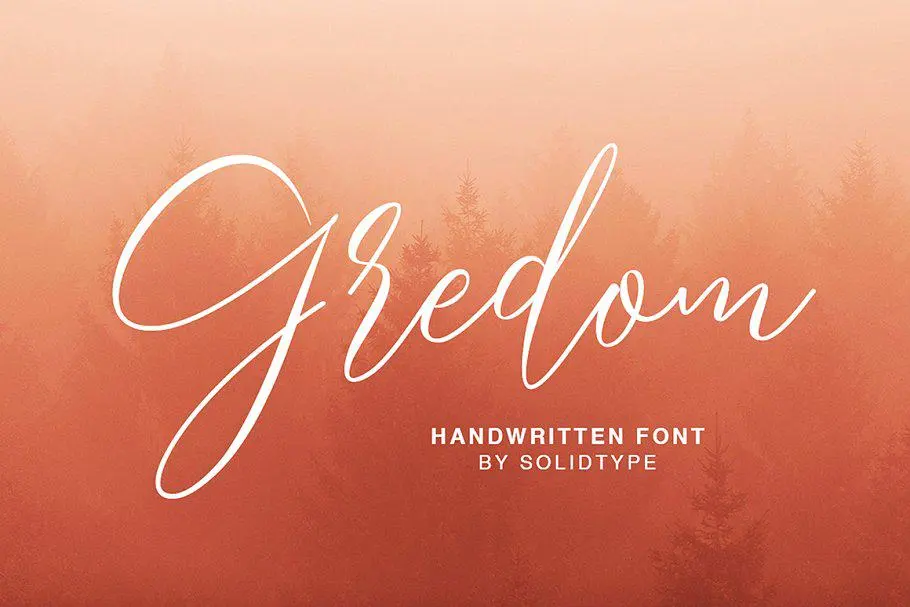
Gredom Script Font – Download Grátis
A Gredom Font é uma elegante tipografia script moderna que oferece um estilo suave e nuances refinadas. Composta a partir das mãos de um escritor, esta fonte foi projetada para se destacar tanto em aplicações de texto quanto em cabeçalhos. Seu design simples e natural faz dela perfeita para uma variedade de projetos gráficos, desde blogs até cartões de festa e convites de casamento. A Gredom apresenta um aspecto moderno e sofisticado que a torna versátil, atendendo às necessidades dos designers profissionais em busca de uma fonte elegante e conveniente para múltiplos usos. Essa fonte será um excelente complemento para suas próximas criações gráficas, oferecendo tanto estilo quanto legibilidade perfeita para qualquer projeto que precise de um touch único e sofisticado.